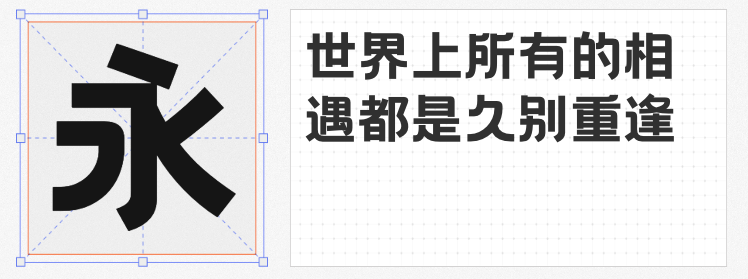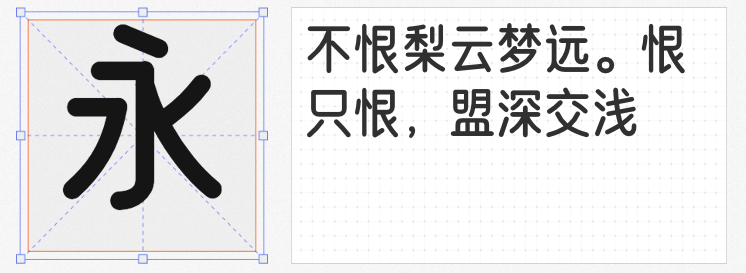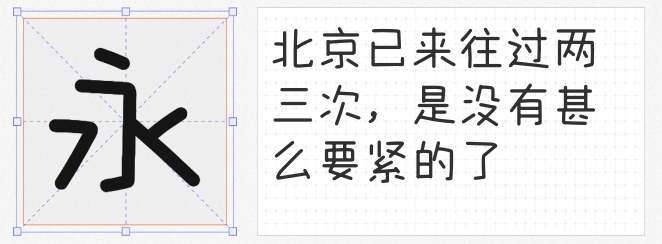
在短视频内容同质化的今天,一款兼具辨识度与亲和力的字体,往往能成为提升完播率的“隐形推手”。本文精选四款免费可商用的创意字体,它们摒弃繁复装饰,以简洁线条传递清新可爱的气质,助力短视频、新媒体内容实现视觉升级。
这款窄长瘦高的斜体字,以80年代美术字为灵感,在几何秩序间找到平衡点。其倾斜角度自然流畅,笔画粗细过渡柔和,既保留手写体的灵动感,又具备现代字体的简洁性。适用于美食探店、生活Vlog等场景的标题设计,用得意黑斜体呈现,能传递温馨治愈的氛围,提升信息传递效率。
以“健康体态”为设计理念,这款字体通过纵向拉长的结构与硬挺的转角曲线,打造出轻快时尚的视觉效果。圆润弧度中暗藏棱角的设计,让字体在可爱之余不失专业感。特别适合健身教程、健康科普类短视频的标题与字幕,例如运动博主分享“7天瘦腰计划”时,用健康体呈现关键数据,既能强化“科学减脂”的主题,又能通过纤细字形降低视觉压迫感,提升观众阅读舒适度。
将图形设计法则融入黑体框架,这款字体通过优雅弧线打破传统黑体的呆板印象。方正饱满的字形中暗藏张力,既适合作为正文字幕保持画面整洁,又能通过局部放大突出重点信息。例如旅行博主拍摄“江南水乡漫游指南”时,用文艺黑呈现景点名称,弧线处理与古风建筑形成呼应,让字体成为画面中的隐形美学元素。
如其名所示,这款字体以风趣错落的字形与多元笔画设计,打造出轻松玩趣的视觉风格。20923个GBK编码字符覆盖各类使用场景,从表情符号到生僻字一应俱全。适合游戏解说、搞笑段子等年轻化内容,例如电竞主播直播时用玩酷体呈现“五杀时刻!”,夸张的笔画错落能瞬间点燃弹幕氛围,强化内容互动性。
在版权风险日益严峻的短视频领域,选择一款合法合规的免费字体,既是对原创者的尊重,也是对内容安全的保障。这四款字体以简洁为底色,以创意为点缀,用清新可爱的风格重构信息传递方式——让字幕不再是被忽视的配角,而是成为吸引用户停留的关键视觉钩子。